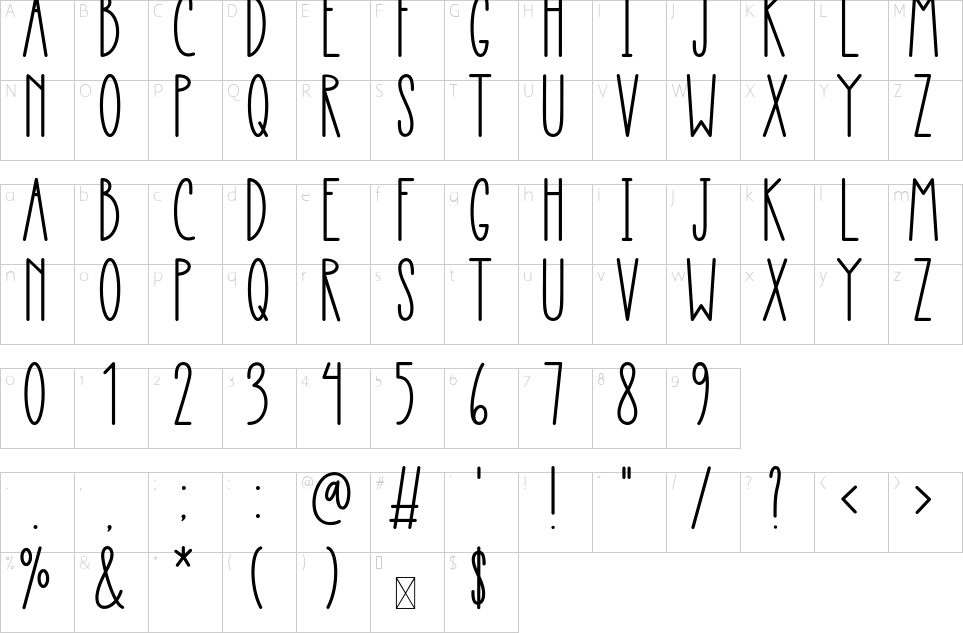
A fonte Salt Shaker, disponível gratuitamente para Windows e Mac, é um projeto criado pela Jimtype Studio. Suas linhas clean e elegantes tornam Salt Shaker perfeito para estilos de design gráfico moderno e minimalista. Desde seu lançamento, o font foi baixado 254 vezes, indicando sua adequação para uma ampla variedade de aplicações, desde logotipos até design editorial. Seja para aqueles que buscam um estilo minimalista ou para aqueles que desejam uma fonte mais elaborada, Salt Shaker é uma escolha ótima para quem busca graciosidade e simplicidade em cada letra.